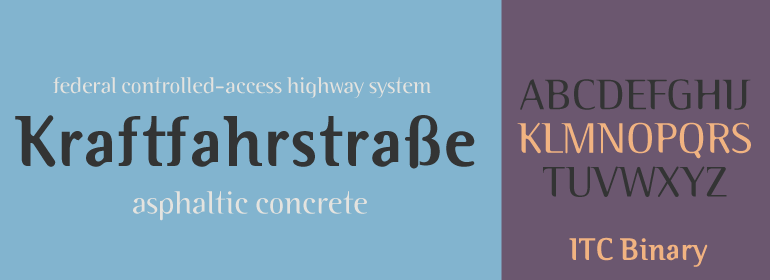
ITC Binary™
ITC Binary™,这款字体结构工整、笔画清晰,兼顾美观与易读性,适用于标题、正文、海报、包装、LOGO 等多种场景。字形优雅稳定,风格百搭耐看,适配日常排版与创意设计,让文字呈现更舒适、更具质感。ITC Binary™一笔一画,皆是细节,以均衡的比例、流畅的线条打造舒适视觉体验,字形端正大气,风格简约现代。无论是商业设计、品牌宣传还是日常排版,都能轻松驾驭,让文字更有格调与力量。ITC Binary™字体下载。
ITC Binary由Mauricio Reyes于1997年设计,是一种具有明显笔划对比的半衬线字体。这款字体的一个显著特点是,许多小写字母的字形看起来像是缺少一小块儿,无论是在基线还是x字高。将字母设置在一起会产生波纹的感觉,以此来引起读者的注意。Binary是一款保守、优雅的字体,字体大小应该使用10pt或更大,且仅用于标题和短到中长的文本。
ITC Binary was designed by Mauricio Reyes in 1997 as a semiserif font with a pronounced stroke contrast. A distinguishing characteristic of this font is that many of the lower case letters seem to be missing a small piece of their forms, either at the base line or x-height. Setting the letters together makes an impression of waviness which draws the attention of the reader. Binary is a reserved, elegant font which should be used in point sizes of 10 or larger and only in headlines and short to middle length texts.